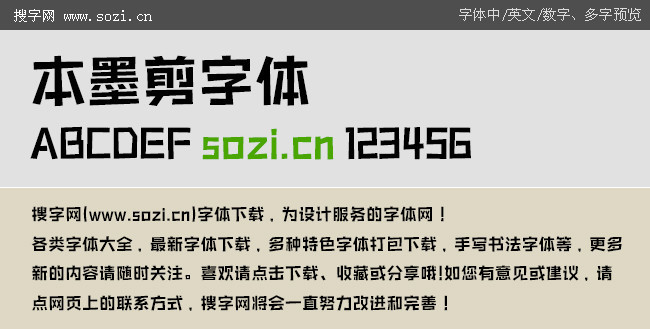
本墨剪字體
搜字網(wǎng)提供一款本墨剪字體中文藝術(shù)字體下載,本墨剪字體是本墨字庫全新推出的一款剪紙體,字體厚重而端正,給人十分沉重的藝術(shù)字體體驗(yàn),自帶加粗和黑體,讓文字更加醒目。適用于書籍設(shè)計、報紙標(biāo)題、畫冊設(shè)計,網(wǎng)頁設(shè)計等應(yīng)用。